黑体字体是一类经典又常用的字体,具有整齐划一的笔划,结构严谨,运用十分广泛,下面给大家分享两款来自三极字库的新字。
三极罗丽黑字形风格舒展柔和,起笔收笔皆为圆,折笔刚柔并济细节饱满,撇捺圆润柔美而又简洁明快,整体时尚而又不失端庄优雅。本款字体拥有3个不同的字重,适用于品牌标志、招牌、包装、广告、游戏、设计等众多场景应用。
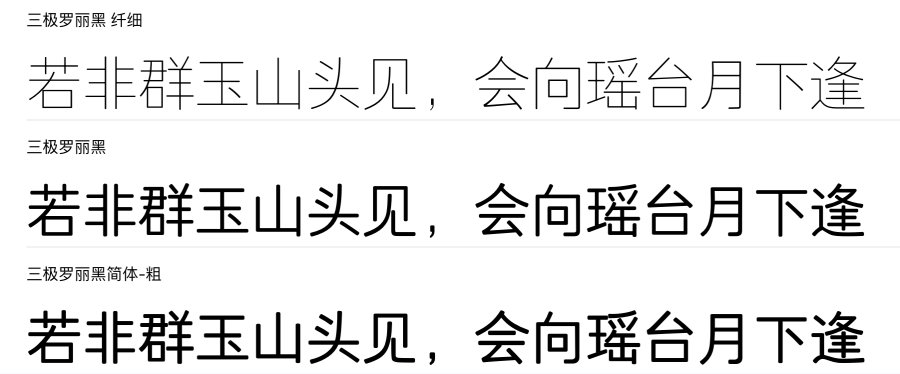
三极团结体是家族字体。这款字体中宫偏小,显得瘦长,撇捺犹如丝带修长,比较有年代感,整体字形方正,笔划制作精良,刚柔相济,简洁有力。适合手机屏显,儿童杂志,玩具包装,标题,广告,招牌等场景中。目前已经在字体视界上线了两个不同的字重,后续将为您不断更新,尽请关注。